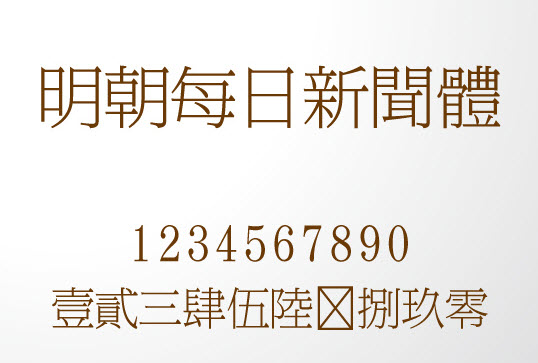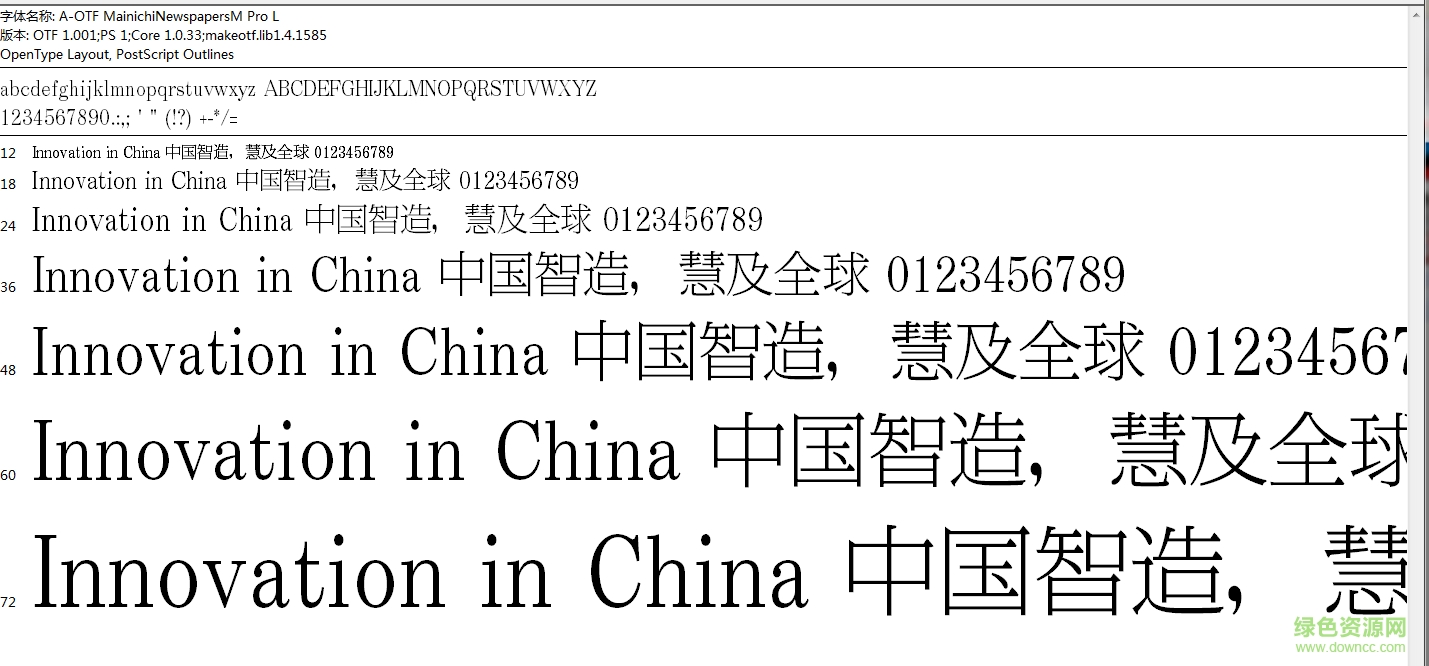
新聞明朝體是一款好用的繁體字體,字體非常的工整,筆畫纖細,非常的秀氣,與一般報紙雜志的字體比較類似,歡迎喜愛的朋友到綠色資源網(wǎng)下載體驗!
新聞明朝體是指宋體字在日本的稱呼,在臺灣和韓國也有明朝體的叫法。漢字的計算機Font技術(shù)最初由日本開發(fā),傳至臺灣,臺灣沿用了日本明朝體的稱呼。
《每日新聞》是日本非常普遍的一份報紙,也是日本歷史最悠久的報紙,每日新聞明朝體時一款非常適合做標題的字體,字體結(jié)構(gòu)非常不錯,用來設計LOGO字體也是不錯